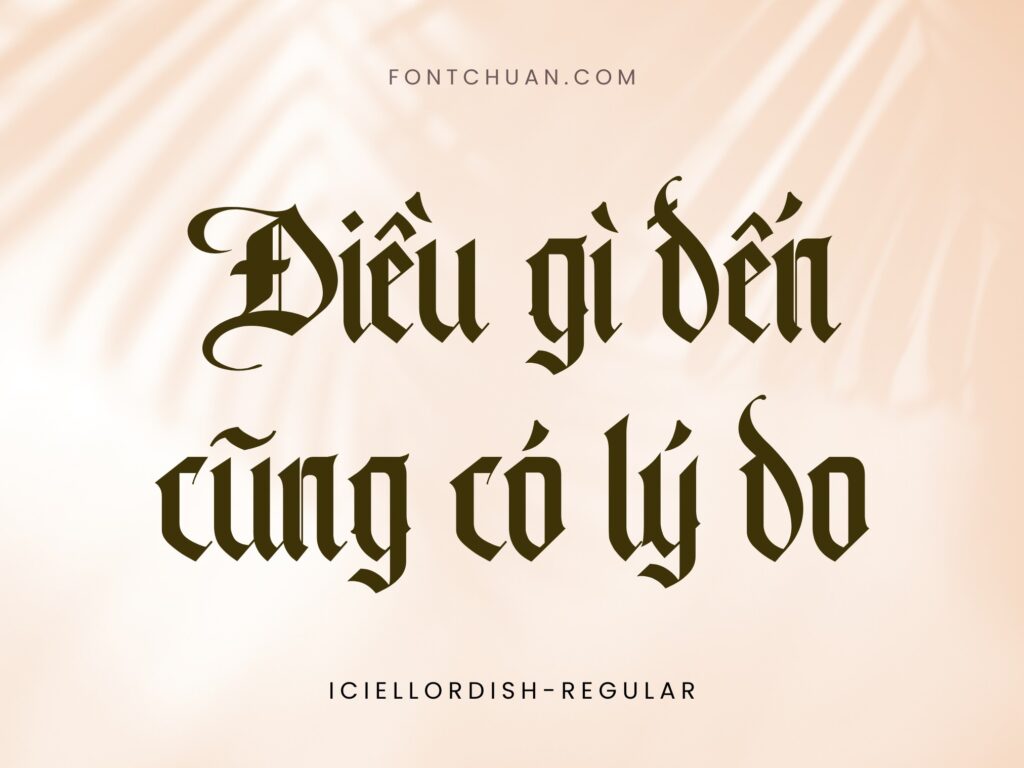
Font iCiel Lordish Việt Hóa
Lordish là một kiểu chữ blackletter độc đáo được thiết kế bởi Creative Media Lab, mang phong cách Gothic cổ điển kết hợp với nét hiện đại. Font này bao gồm 3 trọng lượng: Thin, Light và Regular, cung cấp sự linh hoạt cho các dự án thiết kế đa dạng. Đặc biệt, Lordish đã được Việt hóa bởi Iciel, hỗ trợ tiếng Việt cùng nhiều ngôn ngữ khác, đáp ứng nhu cầu phong phú của người dùng. Thành viên của Font Chuẩn đã sưu tầm và chia sẻ font này, giúp cộng đồng thiết kế ứng dụng dễ dàng trong các dự án của mình.
Về đặc điểm thiết kế, Lordish sở hữu các ký tự đậm nét với đường nét sắc sảo, mang lại cảm giác mạnh mẽ và uy nghiêm. Font này phù hợp cho các thiết kế như tiêu đề, poster, logo, bao bì sản phẩm và các ấn phẩm quảng cáo cần sự nổi bật và cá tính. Ngoài ra, Lordish còn thích hợp cho các ngành nghề như quảng cáo, ẩm thực, thiệp cưới và spa, cùng các sự kiện đặc biệt như làm font chữ lễ hội,  font chữ Trung Thu và Font sinh nhật, Font chữ Halloween, giúp tạo điểm nhấn độc đáo và không khí riêng cho từng dịp.